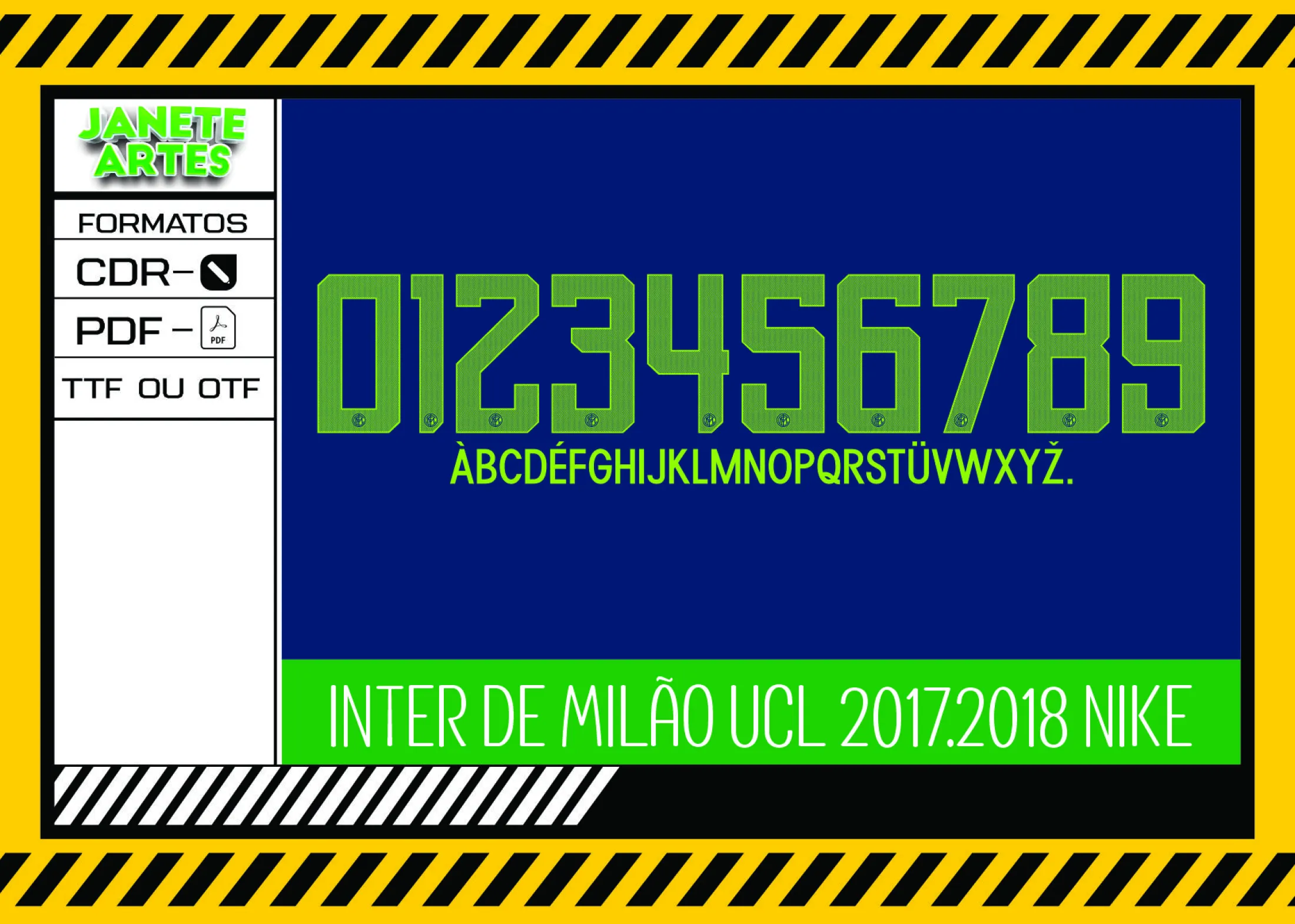
Camiseta unissex preta com logo no peito e estampa grande nas costas da Fonte de Time Tipografia Inter de Milão 2017 - 2018, estilo moderno e esportivo.
Fonte de Time Tipografia Inter de Milão 2017 - 2018 Modelo 02
Arquivo Fonte de Time Tipografia Inter de Milão 2017 - 2018 perfeito para criar camisetas personalizadas com o tema exclusivo e marcante do time, ideal para torcedores e eventos esportivos.
Imagine o momento em que você reúne os amigos para assistir a uma partida do seu time favorito, a emoção aumenta e todos querem demonstrar o orgulho com uma camisa personalizada. Foi assim que a ideia da Arte Camiseta Fonte de Time Tipografia Inter de Milão 2017 - 2018 surgiu: para trazer estilo e identidade ao visual dos torcedores que vivem cada jogo intensamente.
Do futebol às ruas, essa fonte exclusiva reflete tradição e modernidade, dando um toque especial nas camisetas feitas com esse arquivo. Seja para presentear, para uma festa temática ou simplesmente para criar uma peça única, essa fonte oferece possibilidades incríveis.